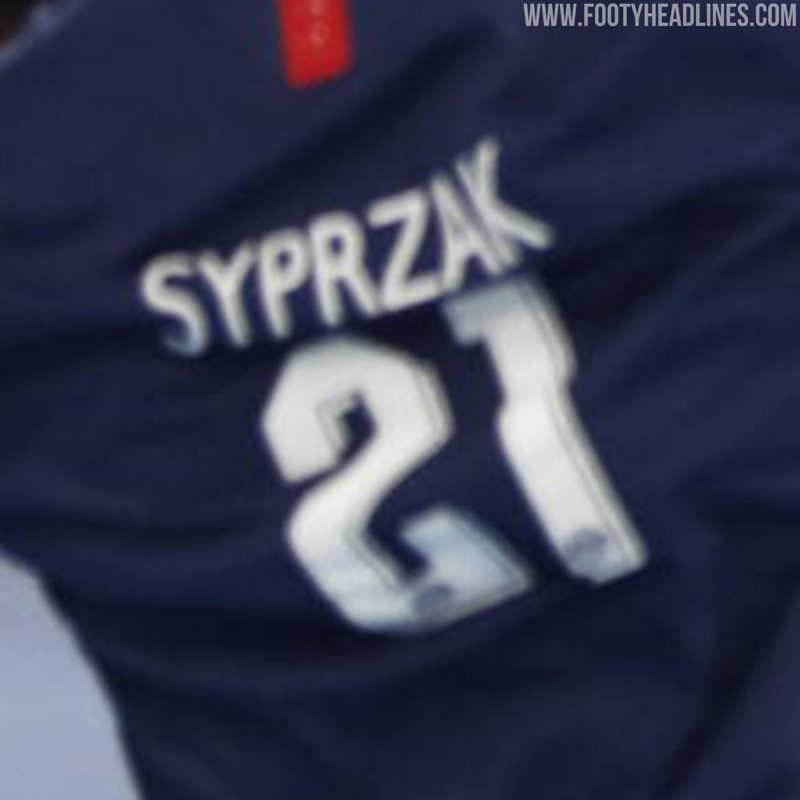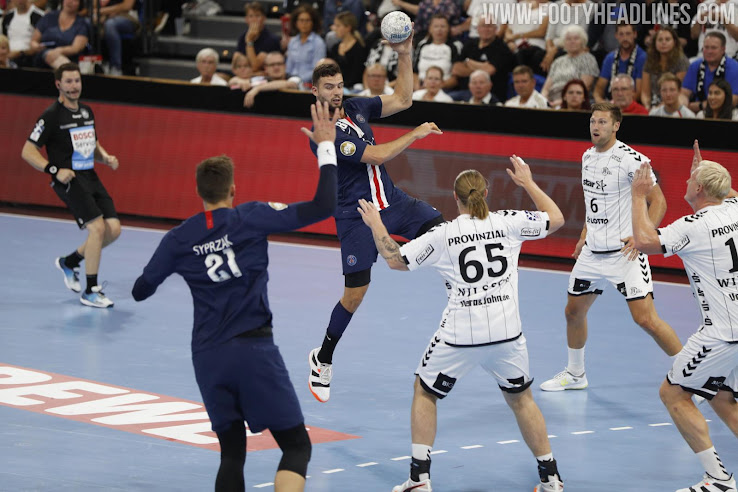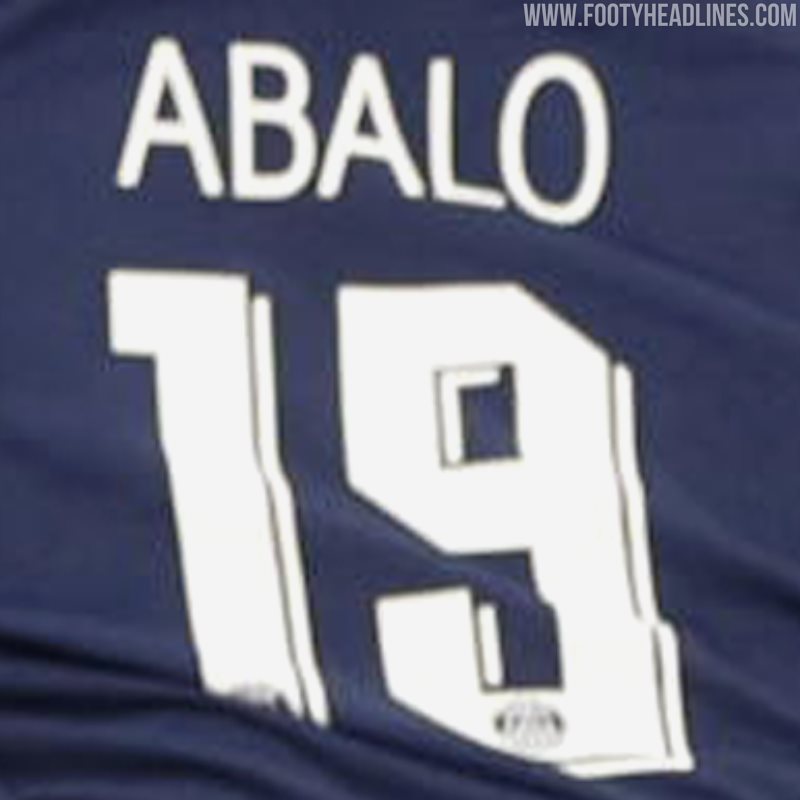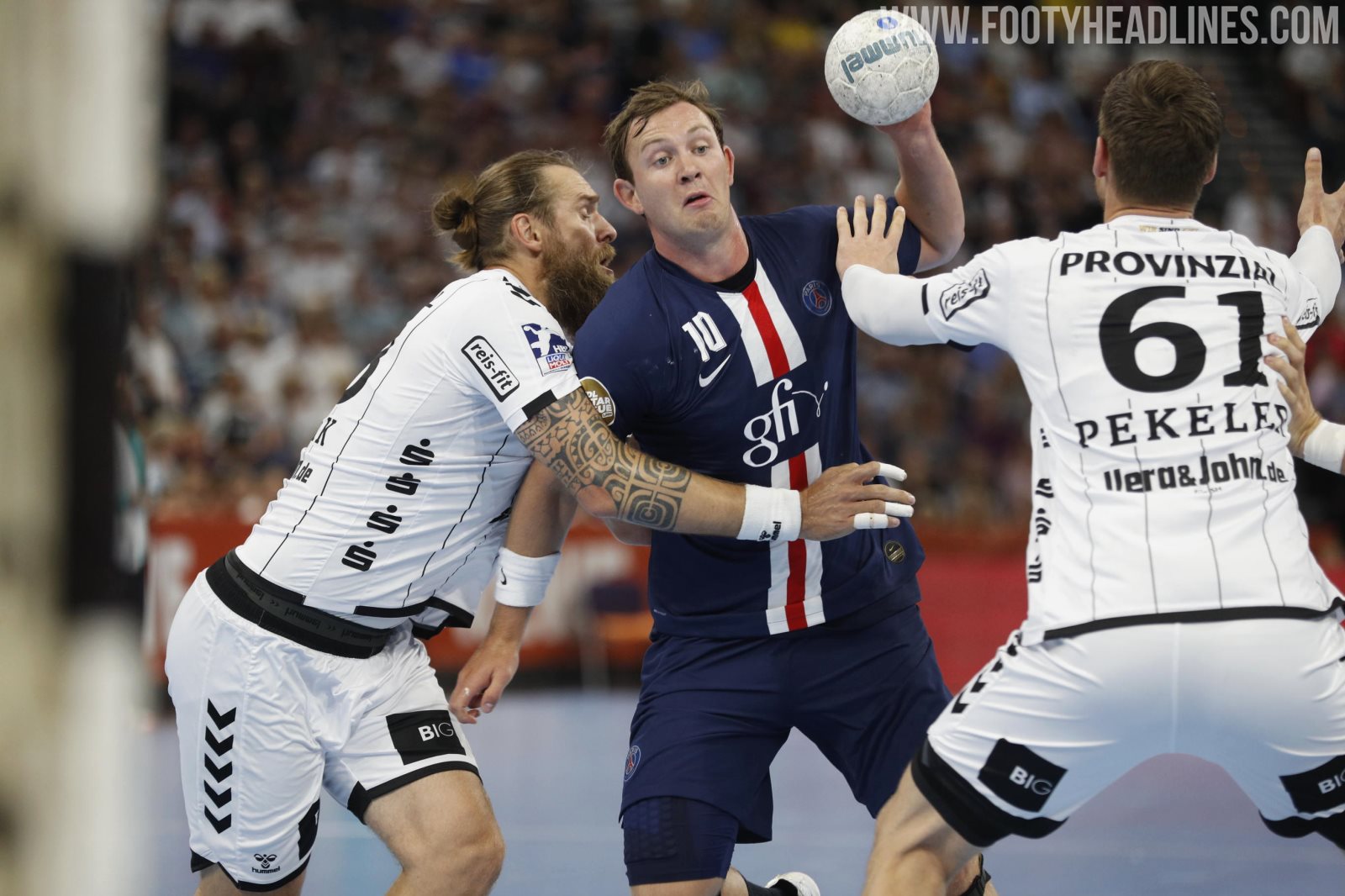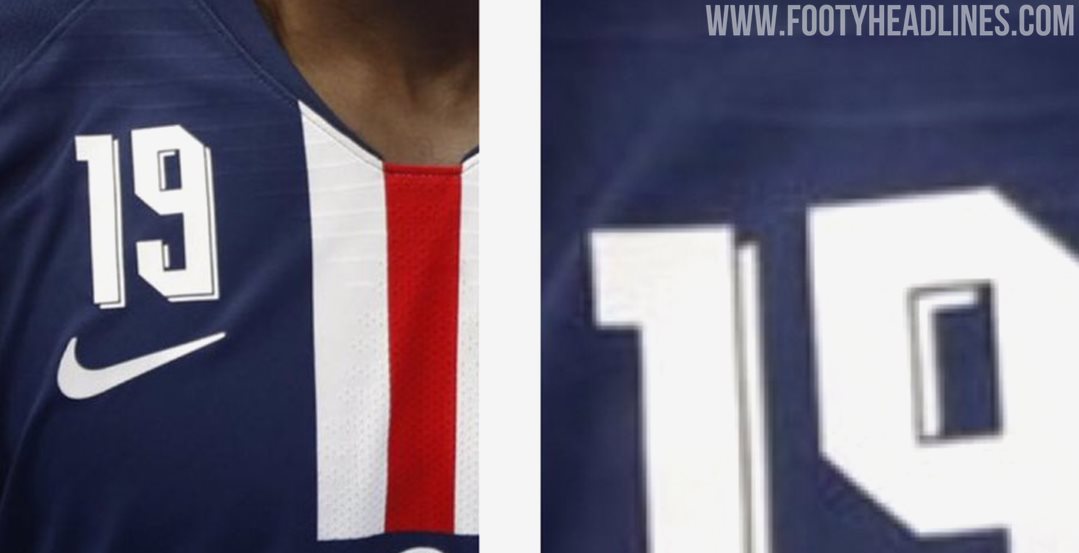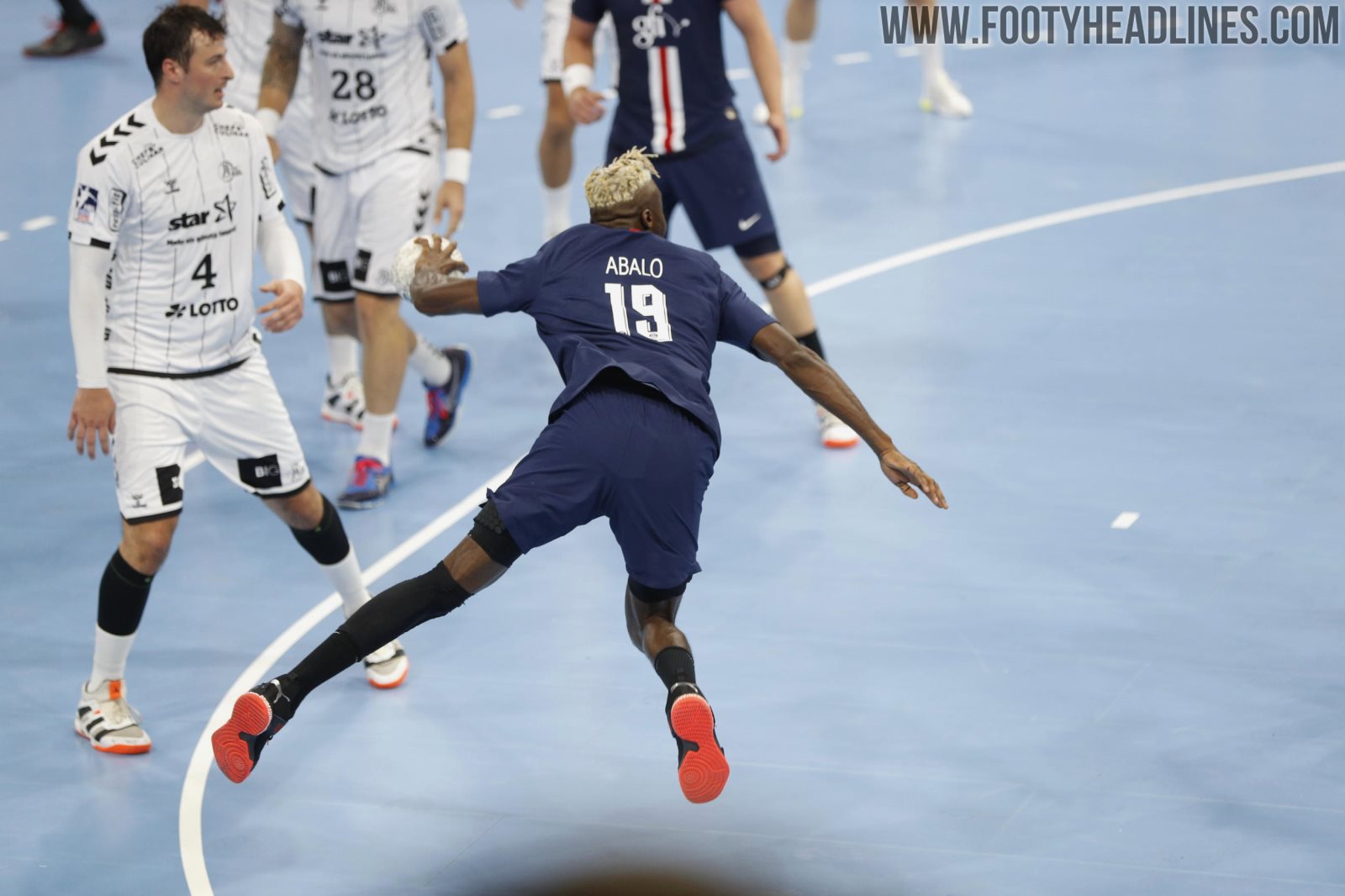
Endlich die richtige? Paris Saint-Germain 19-20 Champions League Trikot-Schriftart enthüllt?
Vor einigen Wochen haben wir einen Artikel über die PSG 19-20 Champions League Schriftart veröffentlicht, wie sie auf der Website von Nike zu finden war. Nun könnte das PSG-Handballteam beim Saisonauftakt die richtige neue Paris Saint-Germain 2019-2020 UEFA Champions League Schriftart vorgestellt haben... (Vielen Dank an @Yoni_Megget für den Hinweis).
PSGs Handballteam sollte die gleiche Schriftart wie die Fußballmannschaft der Pariser verwenden. Wir sind der Meinung, dass die Schriftart von PSG Handball auch diejenige ist, die von PSGs Fußballmannschaft in der UEFA Champions League verwendet wird.
PSG 2019-20 UEFA Champions League Schriftart
Die neue Paris Saint-Germain 19-20 Champions League Schriftart hat ein klassisch angehauchtes Design, das an Schriftarten der 70er und 80er Jahre erinnert.
Das PSG-Wappen befindet sich am unteren Ende der neuen PSG 19-20 Champions League Schriftart. Die Buchstaben der PSG 19-20 Trikot-Schriftart sind einfach.
Paris Saint-Germain wird die maßgeschneiderte 19-20 Trikot-Schriftart im ersten Gruppenspiel der UEFA Champions League 2019-20 erstmals debütieren.